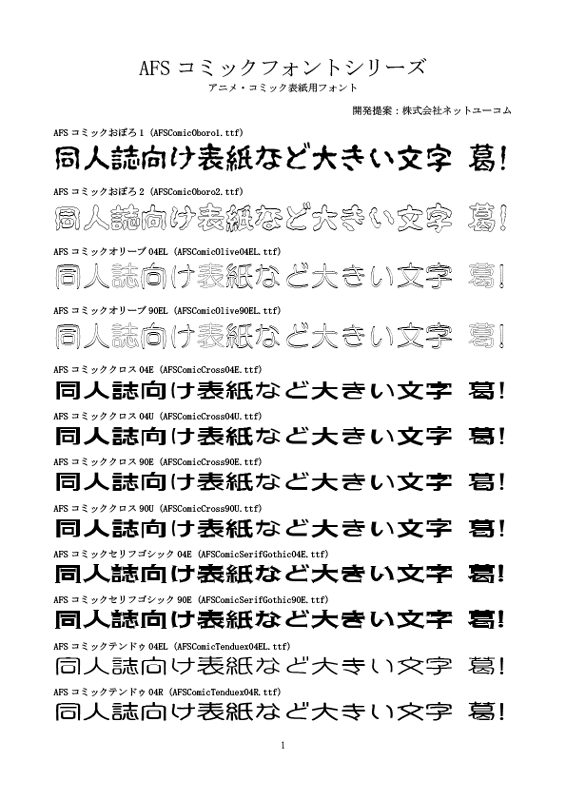
AFSコミックフォントシリーズ(アニメ・コミック表紙用フォントは、株式会社ネットユーコムがお届けする目的別専用フォント。特に大きな字形として表紙や大見出しにご利用頂けるよう基本書体を選び、斜体・袋文字・3Dに字形デザインを加工しました。
基本書体は、おぼろ、オリーブ、クロス、セリフゴシック、フローラ、マカロン、めいげつ、リモーネ、雲水、WindowsOS標準搭載メイリオフォントデザイナーの鈴木竹治によるデザインです。
・字形デザイン
一部書体(オリーブ、クロス、セリフゴシック、フローラ、リモーネ)はファミリーとしてJISX0213の2004字形と1990字形をご用意。例えば「辻」の[一点]しんにょうと[二点]しんにょうの使い分けがフォント選択で可能となりました。フォント名及びフォントファイル名末尾の90と04は、
それぞれ1990年字形と2004年字形を表しています。